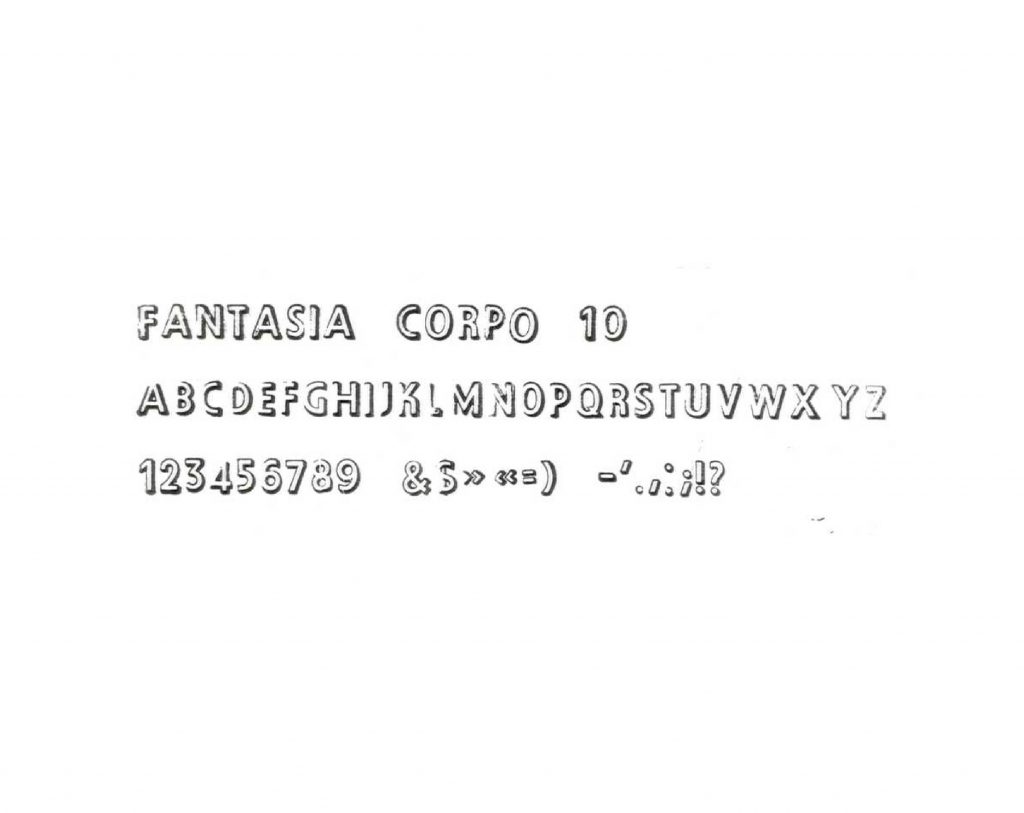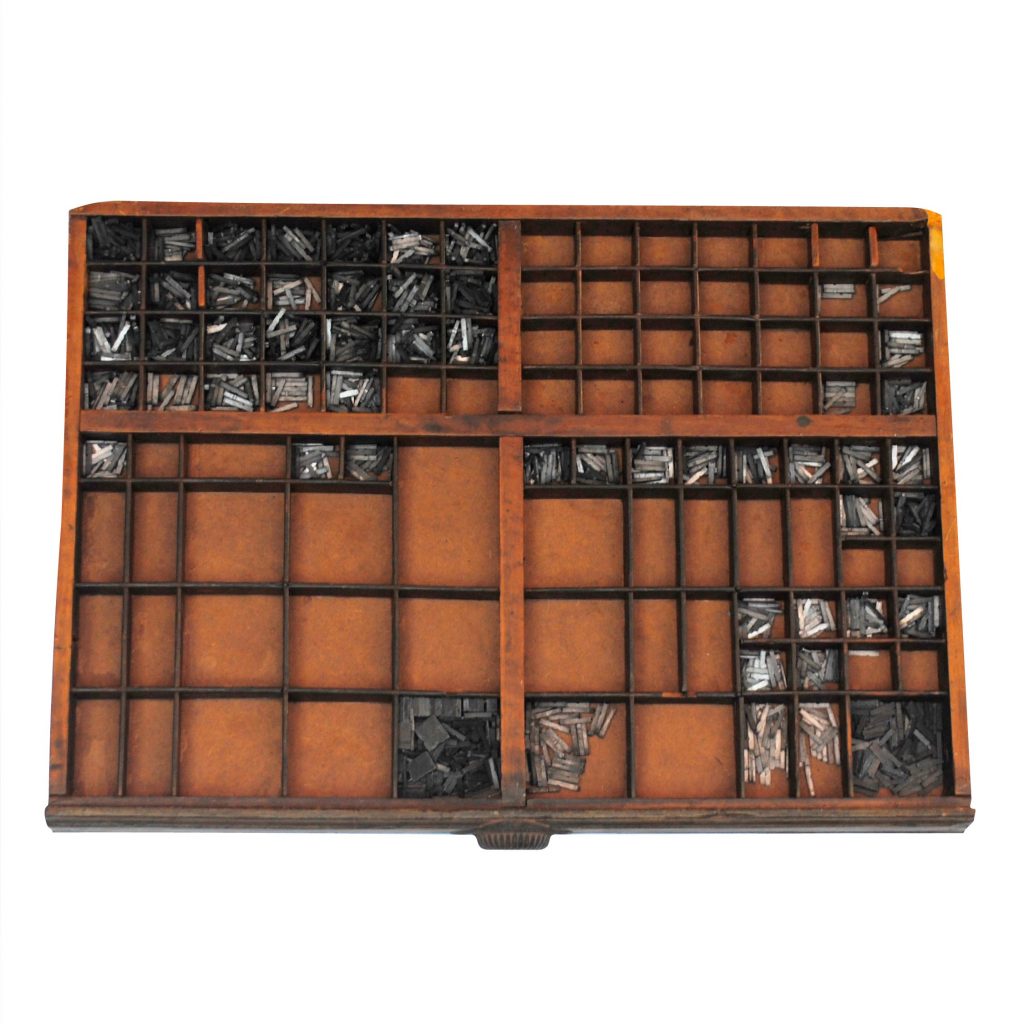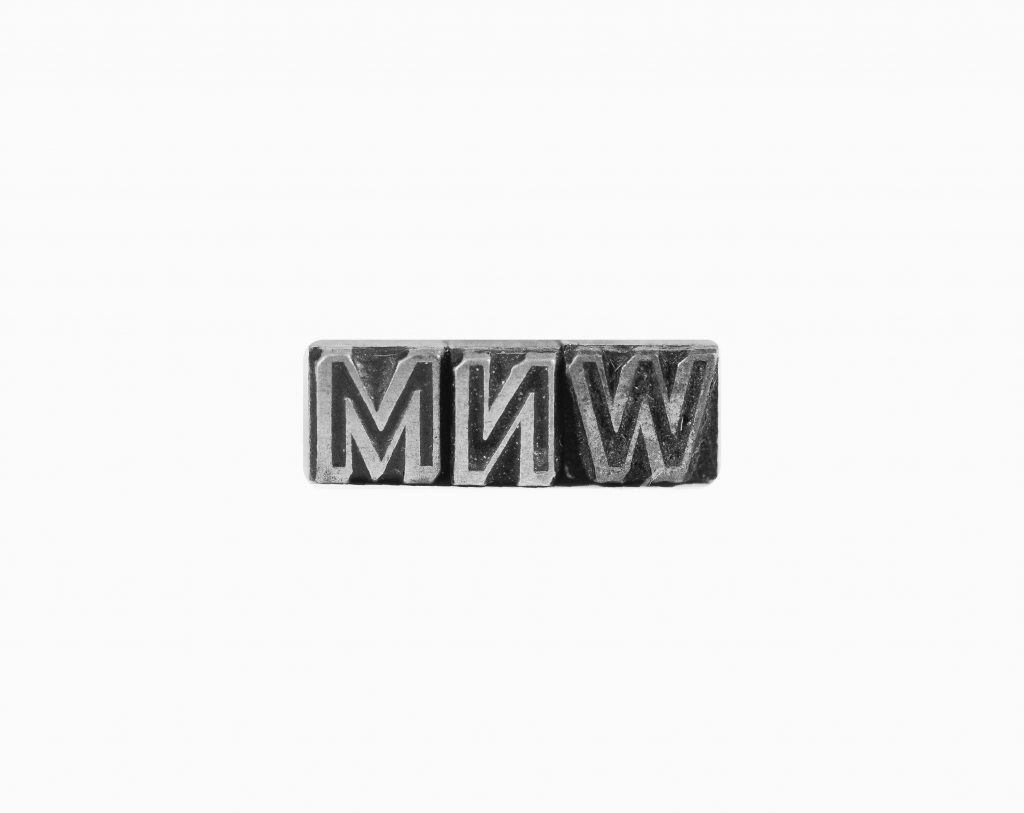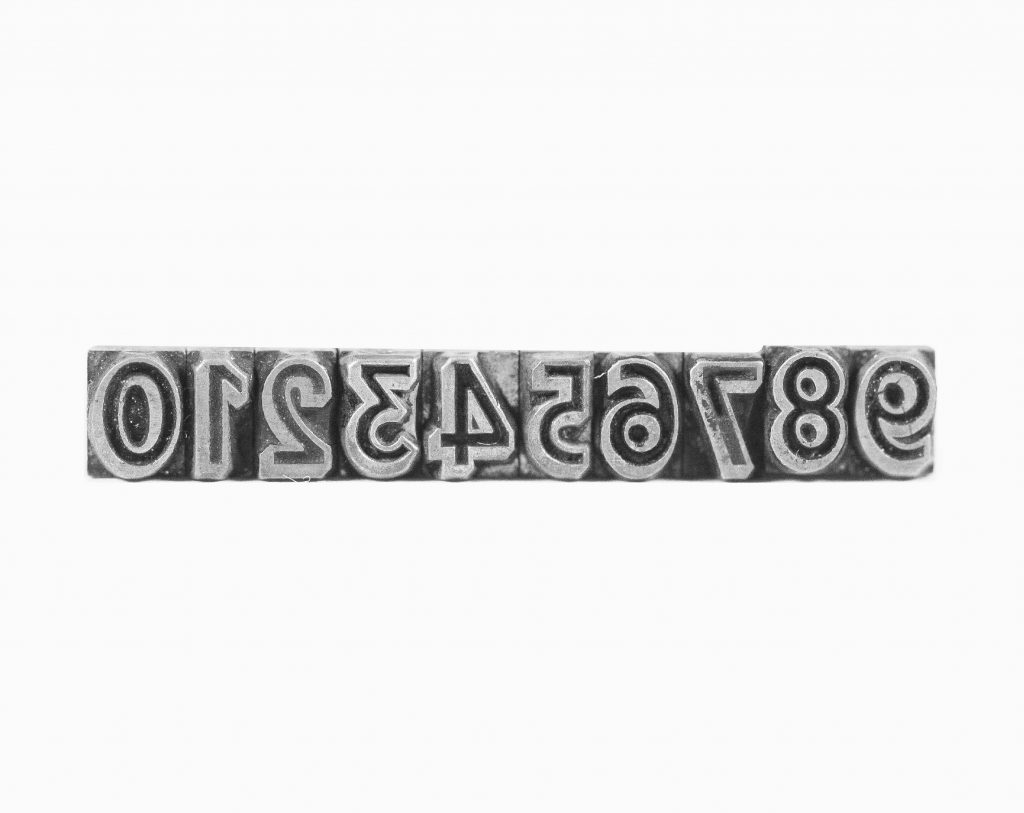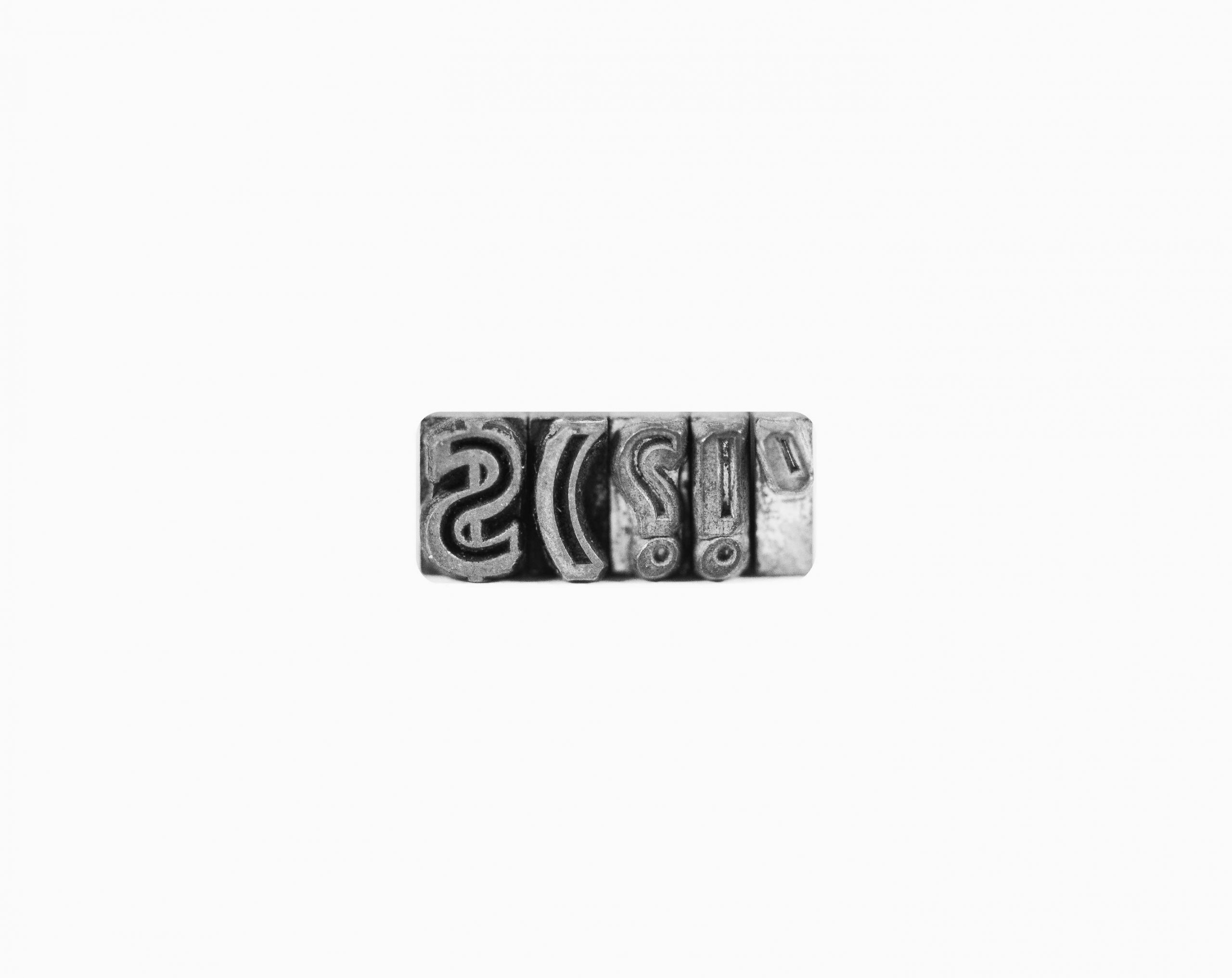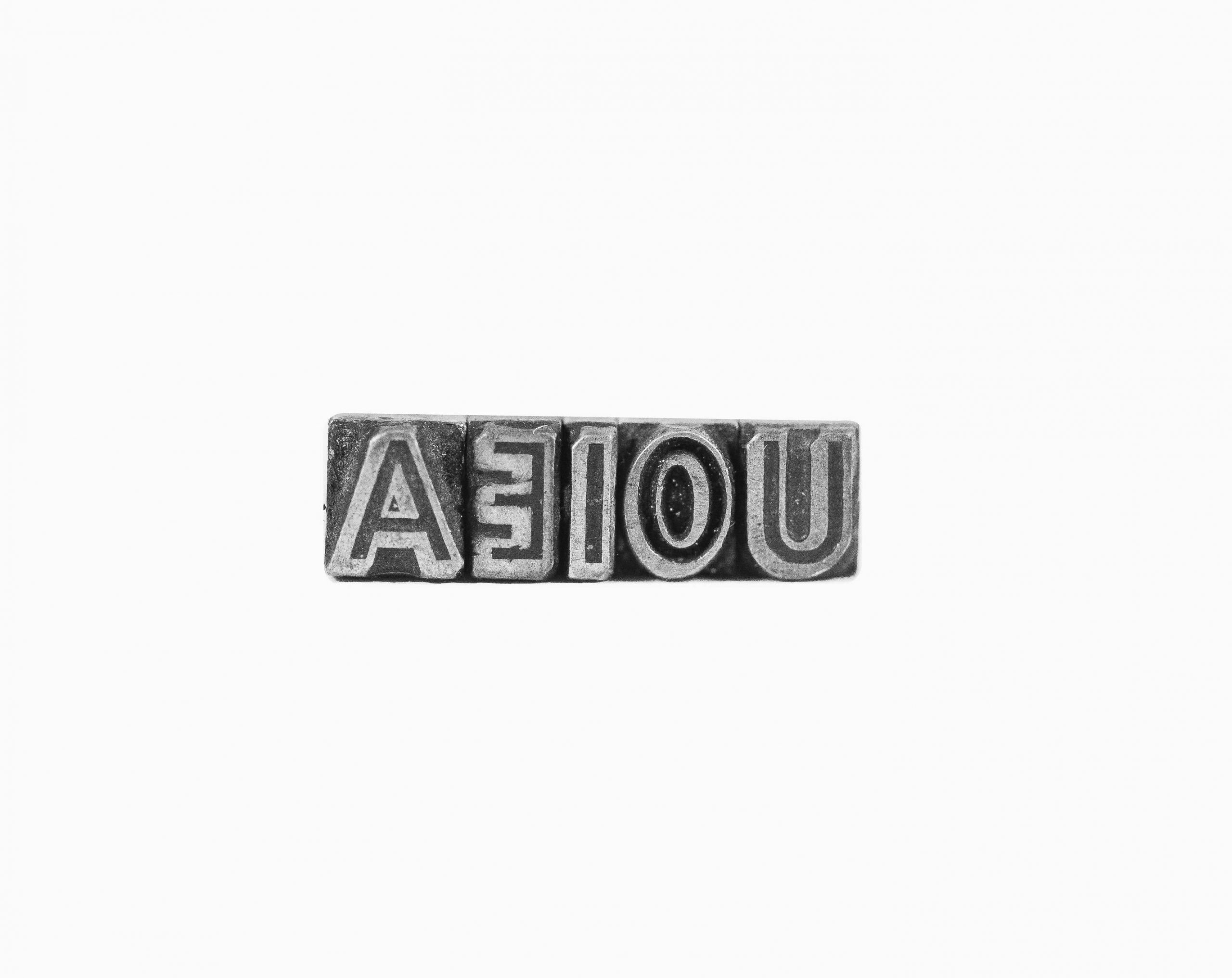
Marcas de uso recorrente; alguns tipos apresentam desgaste na face que pode comprometer a qualidade da impressão.
Maiúsculas | Numerais | Pontuações | Sinais
Sem letras minúsculas.
História do Estilo
Foi encontrada a fonte Orplid em um catálogo da Manig [ca. 1970], que se assemelha com o formato e estilo dos caracteres presentes na gaveta. Segundo a plataforma Fonts in Use, a fonte foi desenhada por Hans Bohn e fundida pela primeira vez pela Klingspor, sediada em Offenbach am Main, na Alemanha, em 1929. No Brasil, foi comercializada pela Manig.